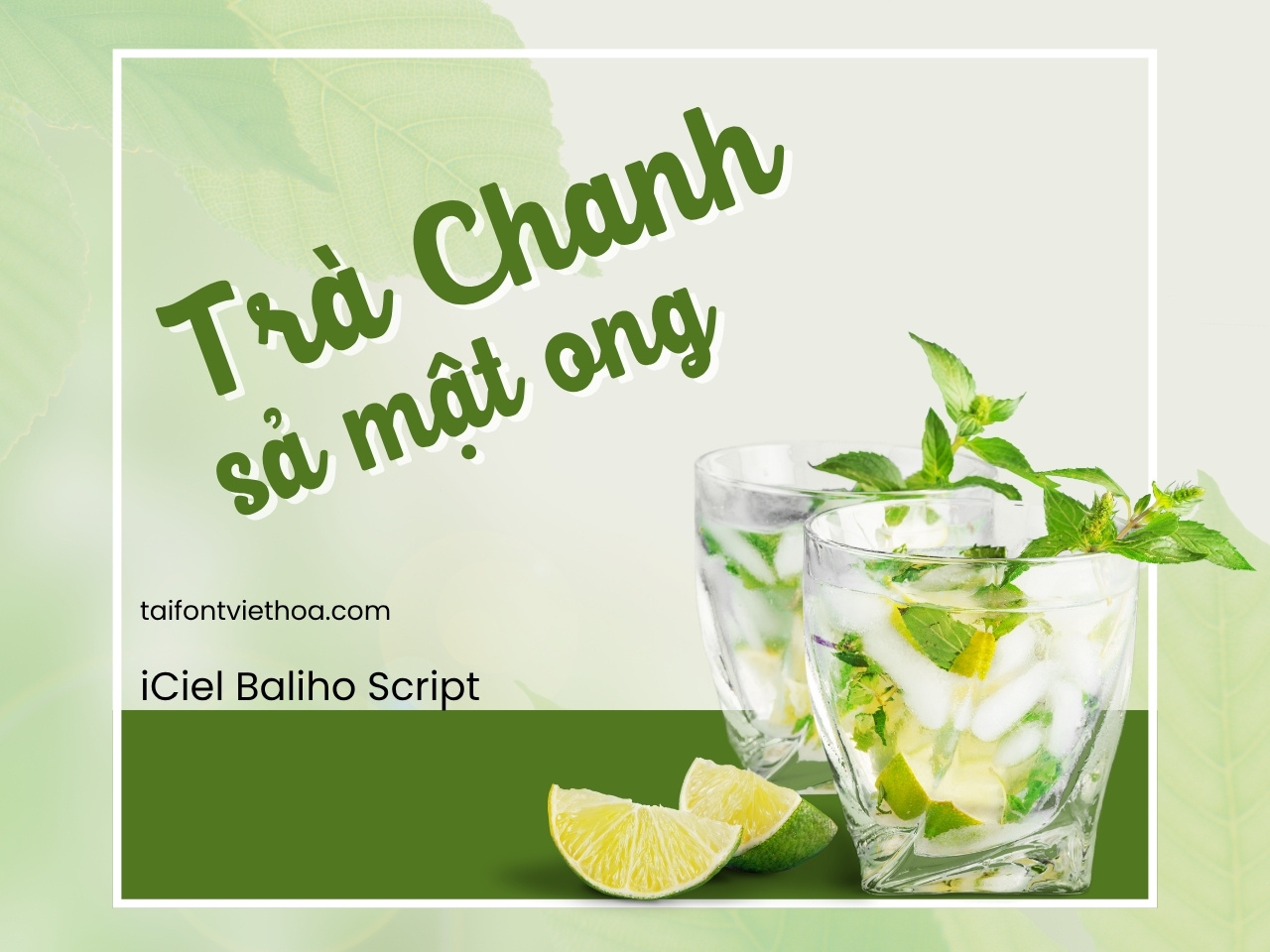
Font việt hóa iCiel Baliho Script
Font việt hóa iCiel Baliho Script, Font mềm mại
Giới thiệu về font iCiel Baliho Script – Nghệ thuật viết tay mượt mà và lôi cuốn
iCiel Baliho Script là phiên bản Việt hóa của một kiểu font viết tay bay bổng, mang phong cách hiện đại nhưng vẫn giữ được chất nghệ thuật cổ điển. Font gốc được phát triển với đường nét mềm mại, đều đặn, được ứng dụng nhiều trong thiết kế thương mại và sáng tạo cá nhân. iCiel đã thực hiện Việt hóa trọn bộ font này, đảm bảo hỗ trợ đầy đủ tiếng Việt cùng hơn 60 ngôn ngữ phổ biến khác trên thế giới.
Đặc điểm thiết kế và ứng dụng của font iCiel Baliho Script
Baliho Script sở hữu cấu trúc script với độ cong tự nhiên, các chữ cái liên kết mượt mà như nét bút viết tay, kèm theo ligatures tùy chỉnh giúp tăng độ sống động và biểu cảm cho từng từ. Các chữ viết có xu hướng kéo dài, tạo nhịp điệu thị giác độc đáo, rất phù hợp để làm tiêu đề, trích dẫn, tên thương hiệu hoặc trang trí in ấn sự kiện.
Font thích hợp với các ngành nghề như ẩm thực, giáo dục nghệ thuật, spa, mỹ phẩm, thiệp cưới, thời trang nữ,… Một số ứng dụng thực tế bao gồm: thiết kế thiệp Valentine, typography lời chúc, menu nhà hàng, poster sự kiện, bìa sổ tay, thiệp sinh nhật, branding cá nhân hoặc fanpage thương hiệu nữ tính.